文字设计的本质是字体语言化、字体图形化的过程,是按照视觉设计规律,对文字进行整体的设计安排,将文字与语言、图像相结合,为信息沟通提供新的平台,为人类构建新的文化思想提供载体,从而提高文字的视觉传达功能。
随着视觉艺术的不断发展,在视觉艺术作品中,文字设计的地位日益加重。为了在二维空间中寻找与创造更为丰富多彩的视觉语言形式,更多的人开始利用文字的视觉传达功能,文字设计进入了新的视觉空间中。本文主要分析了视觉传达设计中文字设计的创新解构与重构。
文字是视觉传达设计的重要元素之一,对其进行加工和编排,使得文字容易被受众识别、理解。在视觉传达设计中,传统文字设计认为文字设计的根本目的在于更好地传递信息,其重视文字的基本功能,在遵循设计形式美法则及传统美学规律的基础上传递信息,从而满足人们审美的需求。
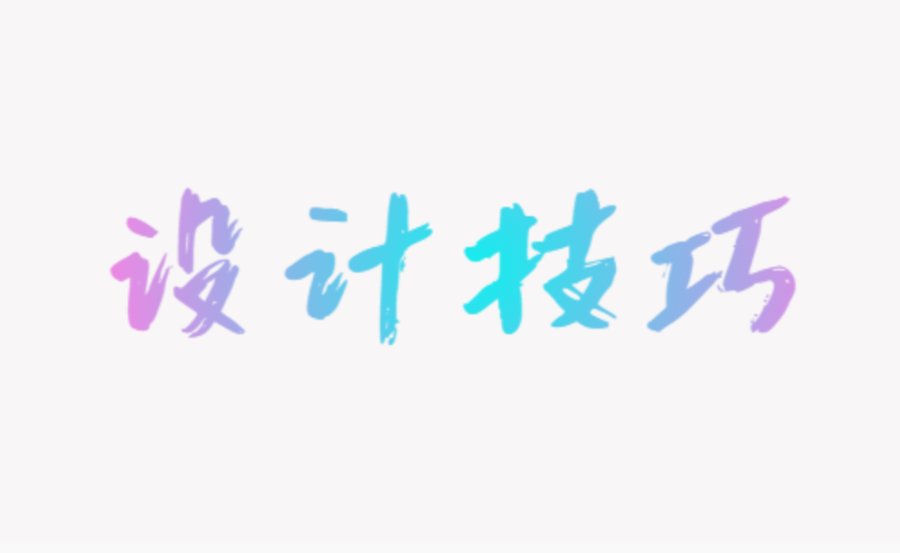
为了给人的视觉印象更加清晰明确,其力求文字效果具有整体统一的视觉表现,讲求的是文字的可识别性和易读性,从而被大众普遍接受。不会因为设计过度,而导致其可读性不强,这也是文字设计创新的基础。但是这种理念容易使读者产生审美疲劳,容易使画面表现形式单一,往往限制了创作者的思维和表现方式。因此,我们要进行改革创新,在传统文字设计理念的基础上,赋予文字设计新的生命力。
设计中的解构与重构
解构是图形的重新分解组合的观念与手法,重构是视觉造型语言基本元素的重构。解构为图形新形式的创造提供了新思路,在解构的前提下,重构能够把解构的全部或者若干单元还原成全新的图形。在视觉传达设计中,不管是图片还是文字,通过解构,都能赋予图示化结果以全新的内涵。因此,在视觉传达设计中,文字、图形、色彩等的运用,要结合视觉传达设计本身的性格和文化,增加对图文的解构与重构等手法的运用,才能传达出更深广的内涵和蕴意,促进视觉传达设计,得到更多观众的理解和认可。
解构方法
解构是解构主义者德里达的一个术语,是后解构主义提出的一种批评方法,即“结构分解”。解构文字是把文字本身,运用解构主义的方法,进行分解、消解,或者为了达到特殊的视觉效果,使其与诸如图形、图像等视觉元素进行有意识的重组和拼贴。
“解构主义”提倡高度模糊和凌乱化,反对现代主义的矫饰,反对二元对抗,因此解构文字的核心是破坏、分解。首先,需要用肆意妄为的精神。抛开传统的美学规律所要求的完整和统一,打破完整,破坏约定俗称的规律,形成破碎的空间。打破整体的、完整的形象与意义,为重新构造新的视觉形象提供基础和条件。
在文字设计中,设计者关注的重点是画面各部分之间的充分表达,不再是作品的完整统一。
①文字及内容的合理性被忽视。人们对于画面的关注点从文字内容本身转移到文字图形化的表现上,注意力集中在画面打散的趣味性和对文字非常规的处理上。
②画面呈现出多中心、多视点的格局,文字突破了有限空间的限制。文字解构是在看似凌乱和不规整的表象下,为了达到形散而意不散的视觉效果,字与形、形与形之间都需要存在高度的协调性,并不是文字各个解构和图像之间毫无章法的堆砌。因此,文字解构是设计者对于这个“度”的把握,并不是没有章法和没有度的。
重构方法
由于“重构”是在“解构主义”的破碎中建立起来的另一种模式,因此,“重构”是“解构主义”的进一步延伸与发展,是在“解构主义”思潮影响下一体化的联盟。这种表现手法为文字设计的生存与发展提供了宏大的舞台。
①笔画重构,为了准确的传达信息,在文字不失识别性的基础上,根据视觉设计规律及形式美的法则,按照文字本身的特点,将文字的笔画打散后,进行笔画之间的重构,能够呈现出全新的视觉效果。
首先,笔画共用。为了增加字体的设计感和追求文字造型的生动性,将文字笔画打散重构的同时,把某些具有相似结构的文字共用其中的一个笔画、结构,从而使文字之间呈现出特殊的视觉效果,产生相关性和互动性。其次,笔画图形化。为了使文字设计具有点睛之笔的效果,把文字中某些笔画进行图形化处理,在将文字笔画打散重构的同时,又活跃了画面。另外,笔画缺失。在将文字笔画打散重构的同时,为了呈现出生动和特殊的视觉效果酒瓯,把文字中某些不影响文字识别度的笔画或结构去掉。
②添加和取舍,通常,添加是指在汉字结构之上,不改变文体大结构的情况下,进行装饰性的添加。取舍是指把无关紧要的、在设计中不能体现实际意义的结构去掉,选取文字中必要的、值得保留的结构。添加和取舍是文字重构中比较常用的方法之一。
如:汉字的字形中体现着无限的意境。在缺失掉一些笔画之后,根据人的视觉惯性,很多汉字并没有丢失其能揭示内涵意境的主要结构,依然能够给人感受到文字本身的形体与内涵。甚至有时候在进行取舍重构之后,一些汉字能更加充实地传达出意境,使其形象更加饱满。
③图文重构,为了形成一种新的视觉效果,图文重构是将文字或图像运用某种设计理念、视觉规律进行分解后再结合在一起。图文重构的过程中,为了加强画面表现力,以图文重构的方式,表现出文字和图像等要素局部之间的关系。
例如:重构过程中,为了加强视觉强度,可以运用重构画面的疏密聚散;为了加强画面的视觉表现力,可以运用重构元素的色彩、肌理等视觉效果;为了加强画面的空间关系,可以运用重构画面的结构、韵律等。在重构的过程中,为了使画面的表现形式存在不确定性和偶然性,设计者往往从感性出发,打破空间的前后顺序、理性的因果关系,重感性表现而轻逻辑关系,从而让受众获得一种感观的觉醒。